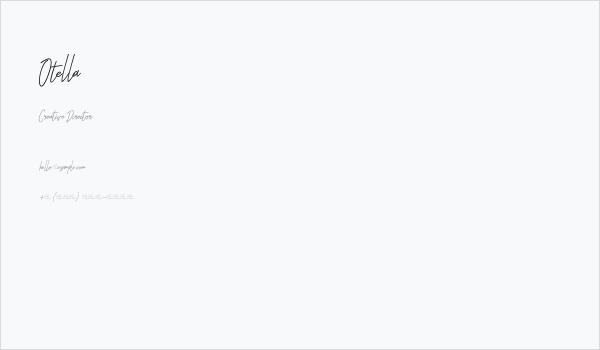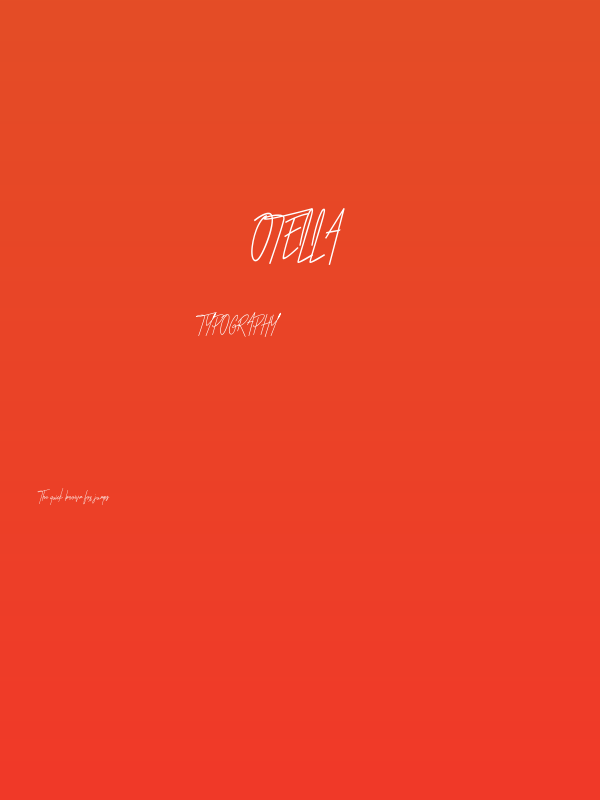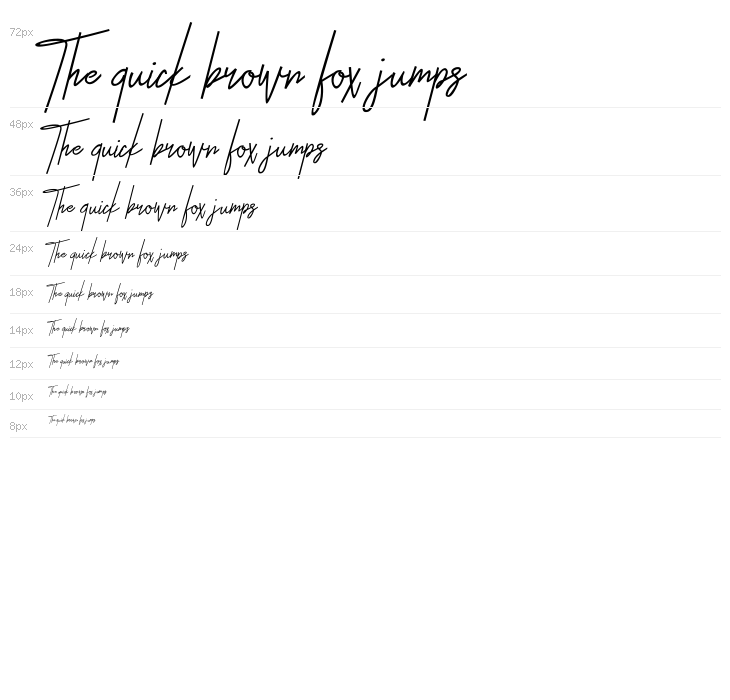
Otella Font
| Cas d'utilisation | Logos, Headlines, Artistic projects |
| Projets proposés | Ideal for invitations, greeting cards, personal branding, and artistic projects. |